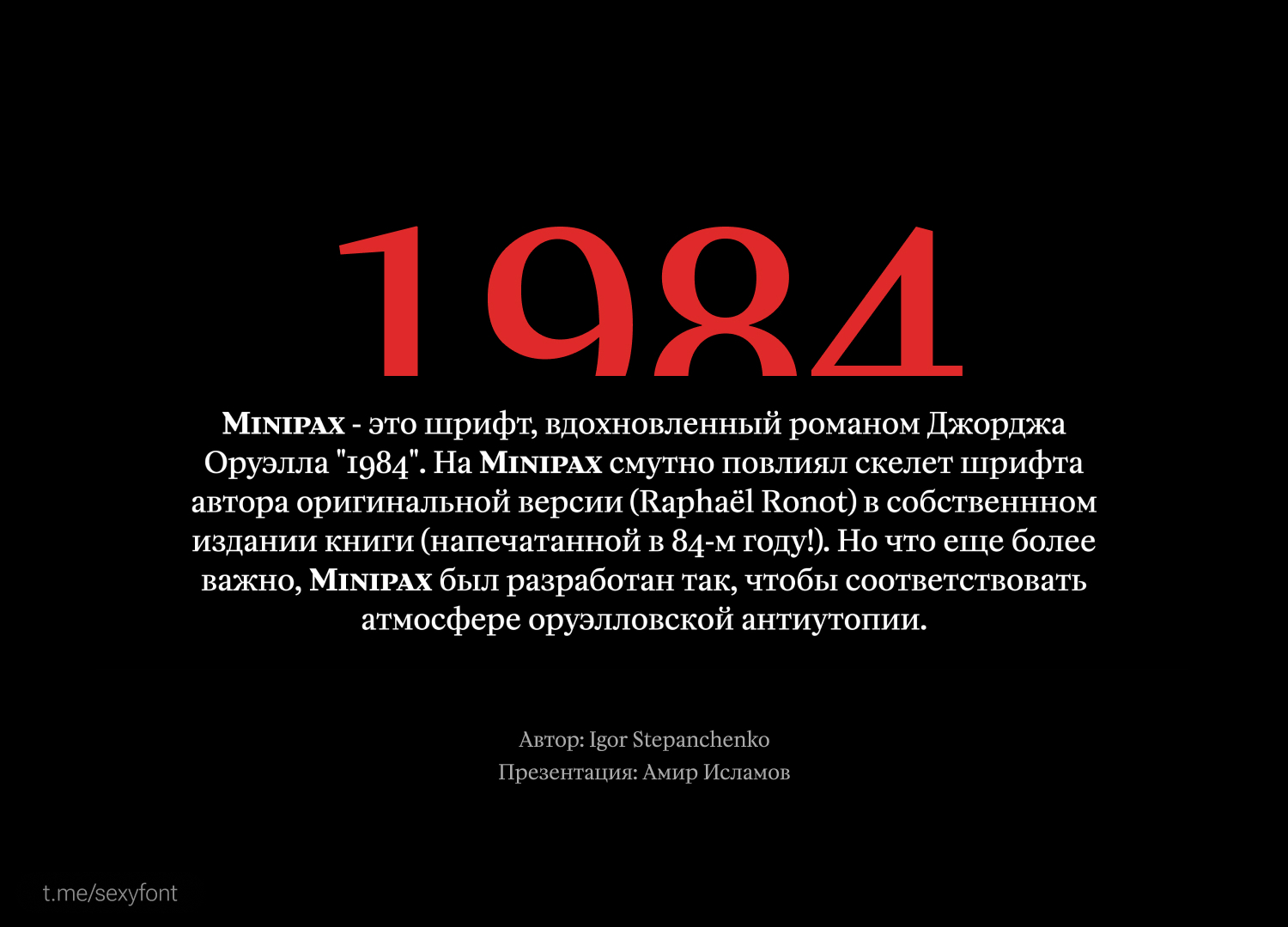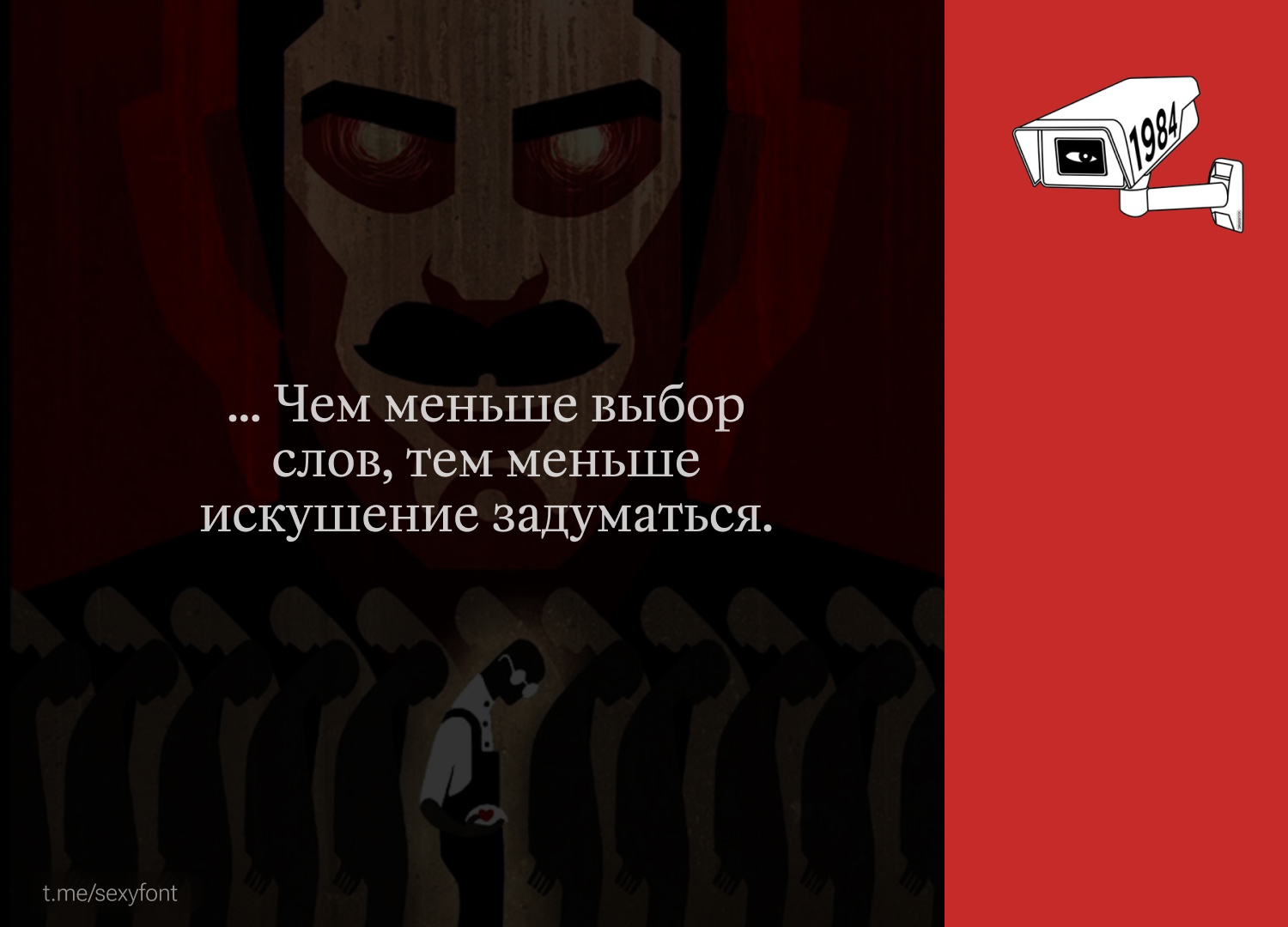
Шрифт Minipax. Кириллица
Я тут начал 1984 читать) И вижу шрифтец, вдохновленный книгой. На мой взгляд книге бы подошел высокий и острый шрифт, а не антиква) Но у автора шрифта была другая задумка. Мое дело презентацию сделать.